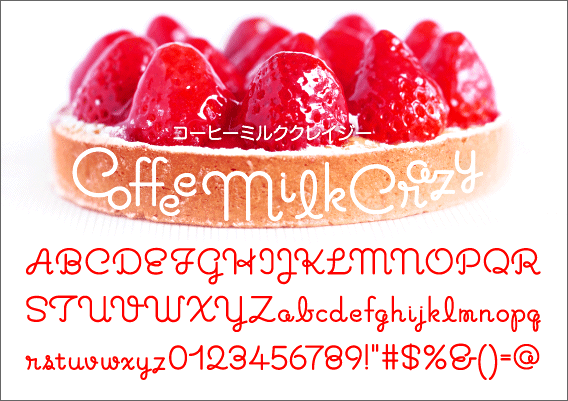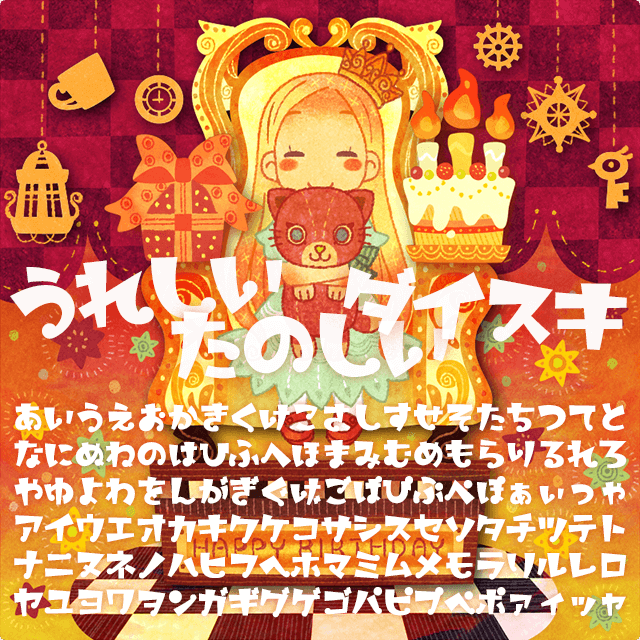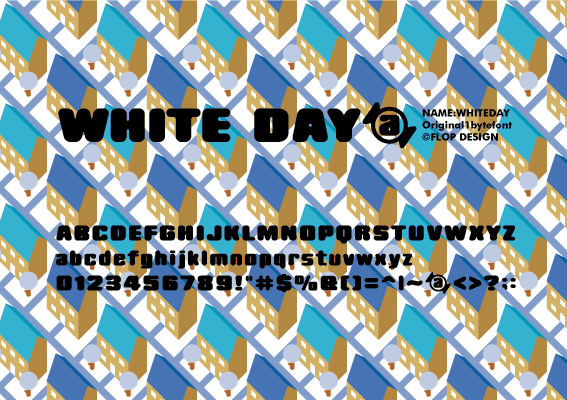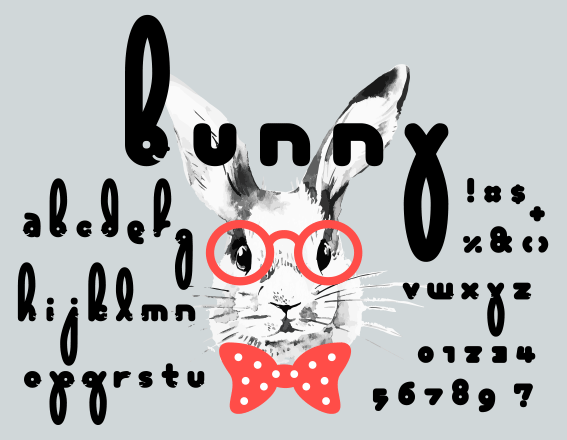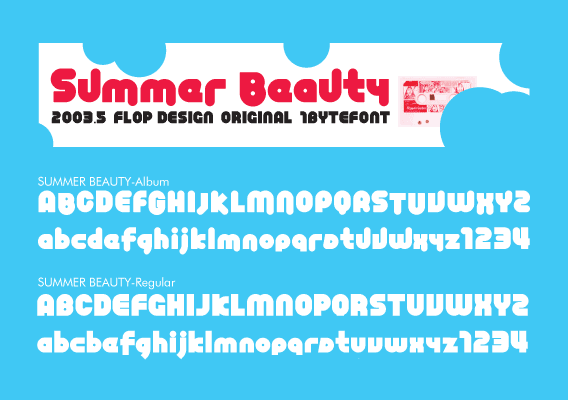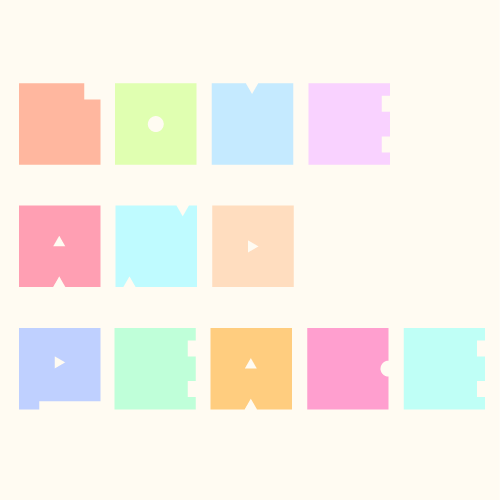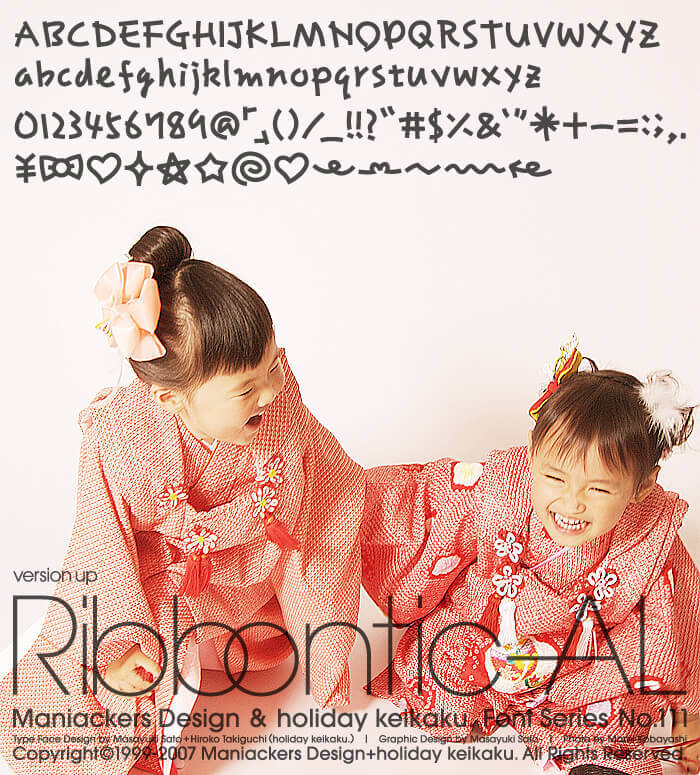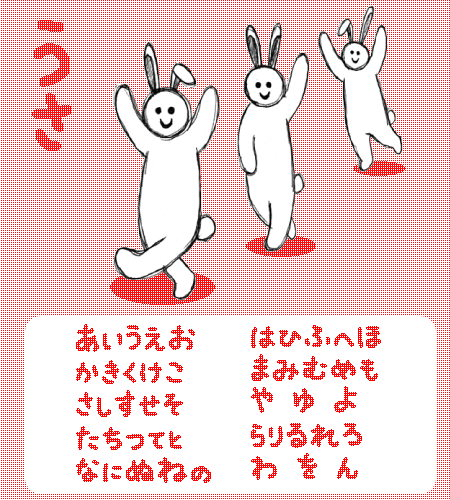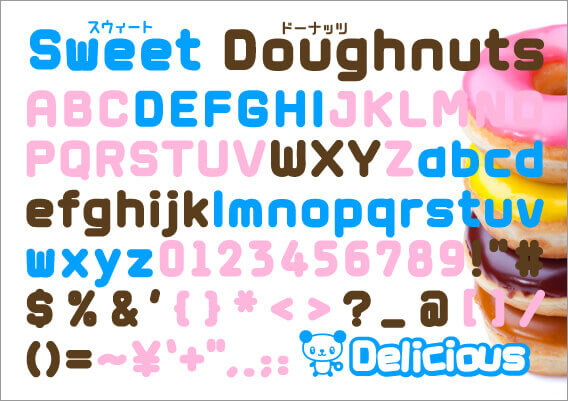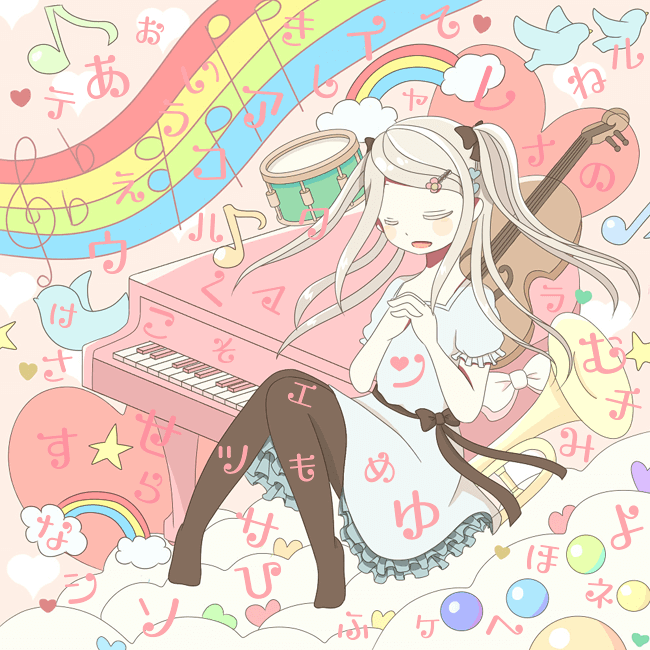
女子が好むガーリーデザインに最適なフリーフォント44選
女性をターゲットにしたかわいいデザインを仕上げるには、配色を意識することはもちろんのことタイポグラフィーも合わせて意識すると、より女子力の高いデザインに仕上がります。ここではガーリーデザインに欠かせない無料ダウンロード可能なフォントを集めました。
252MKSDGB UltraBold – AL
極太丸ゴシック体のフォント。大文字のみ。
AK-ANGEL
文字に天使の羽をつけているかわいいフォント。小文字で打つとそのまま、大文字で打つと陰付きになる。
AK-cookies chocolate
クッキーみたいなフォント。チョコ(黒塗り)とバニラ(白抜き)の2書体。小文字で入力すると点々付きの大文字、大文字で入力すると点々無しの大文字で入力できる。
AK-OSARU H
寝そべった猿のおなかに文字を書き込んだような使い方ができる手書き風フォント。Hはひらがなバージョン。記号は「~」だけ。
AK-OSARU R
上記の「AK-OSARU H」のアルファベットバージョン。記号は「! ? & @」のみ。
Boxboxbox Heavy
ずっしりとした重みのある、木からつくったつみ木のようなフォント。正方形に近い形で、ロゴや見出しなどの利用にピッタリ。
Cherish
文字の中にハートが隠れているフォント。半角英数、一部の記号を収録。
Cherry Bomb
さくらんぼのようにかわいくデザインされたフォント。アルファベット、数字、ひらがな、カタカナ、一部記号が使用可。
Holiday Bold-AL, KT, HR
太めのマジックで書いたようなフォント。ひよこ?のような絵文字も収録。
KFひま字キッズ
げんきな子供たちをイメージして作られたフォント。入力可能な文字は、英数、ひらがな、カタカナ、記号の一部。
Magatama-AL
名前の通り、縄文~古墳時代に装身具として使われていた『勾玉(曲玉)』の独特な造形を元にしてデザインされたフォント。
Mikiyu Font Mokomori-A
手書き風の白抜き文字フォント。アルファベット、数字、記号のみ。
Mikiyu Font Mokomori-B
上記の「Mikiyu Font Mokomori-A」の太文字バージョン。
Milk Choco
太文字で丸々としているかわいいポップなフォント。
Ribbontic 2.0-AL
サインペンで書かれたような手書きフォント。欧文フォントのみ収録。
Silver Lining
文字の中に星が隠れているフォント。半角英数、一部の記号を収録。
U.S.A.
トーンでかかれたようなフォント。うさのイラストも収録。
あかちゃんフォント